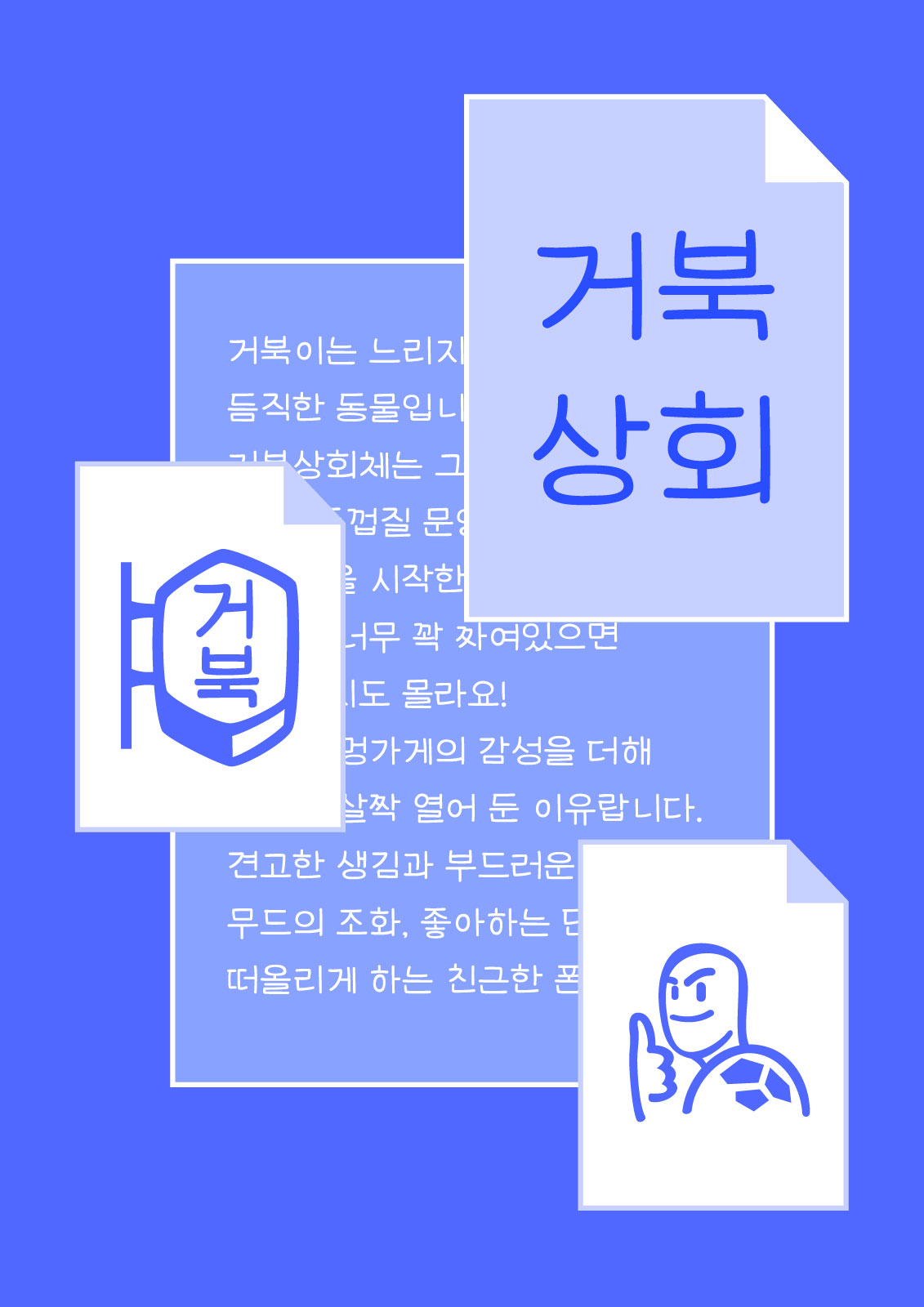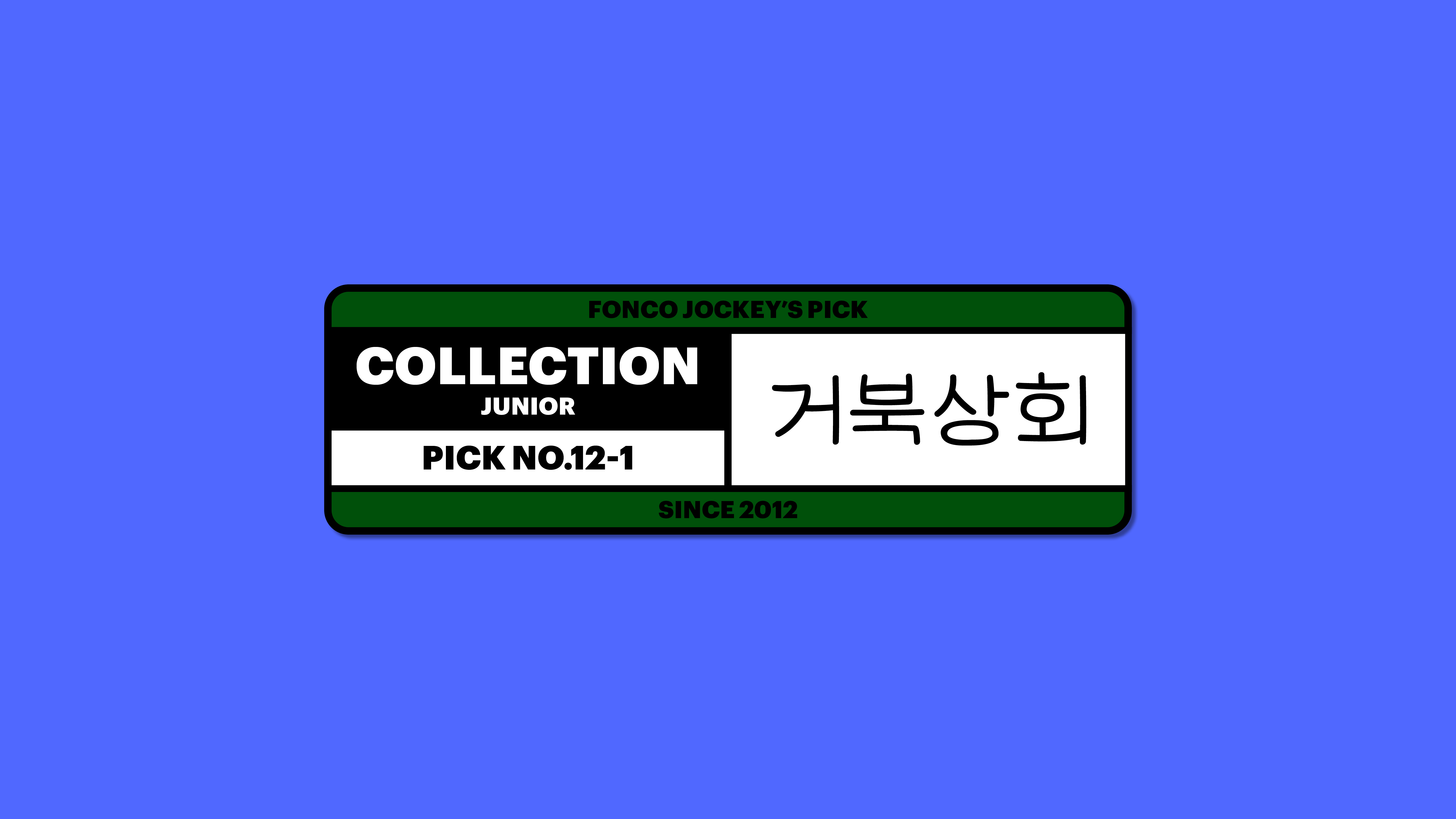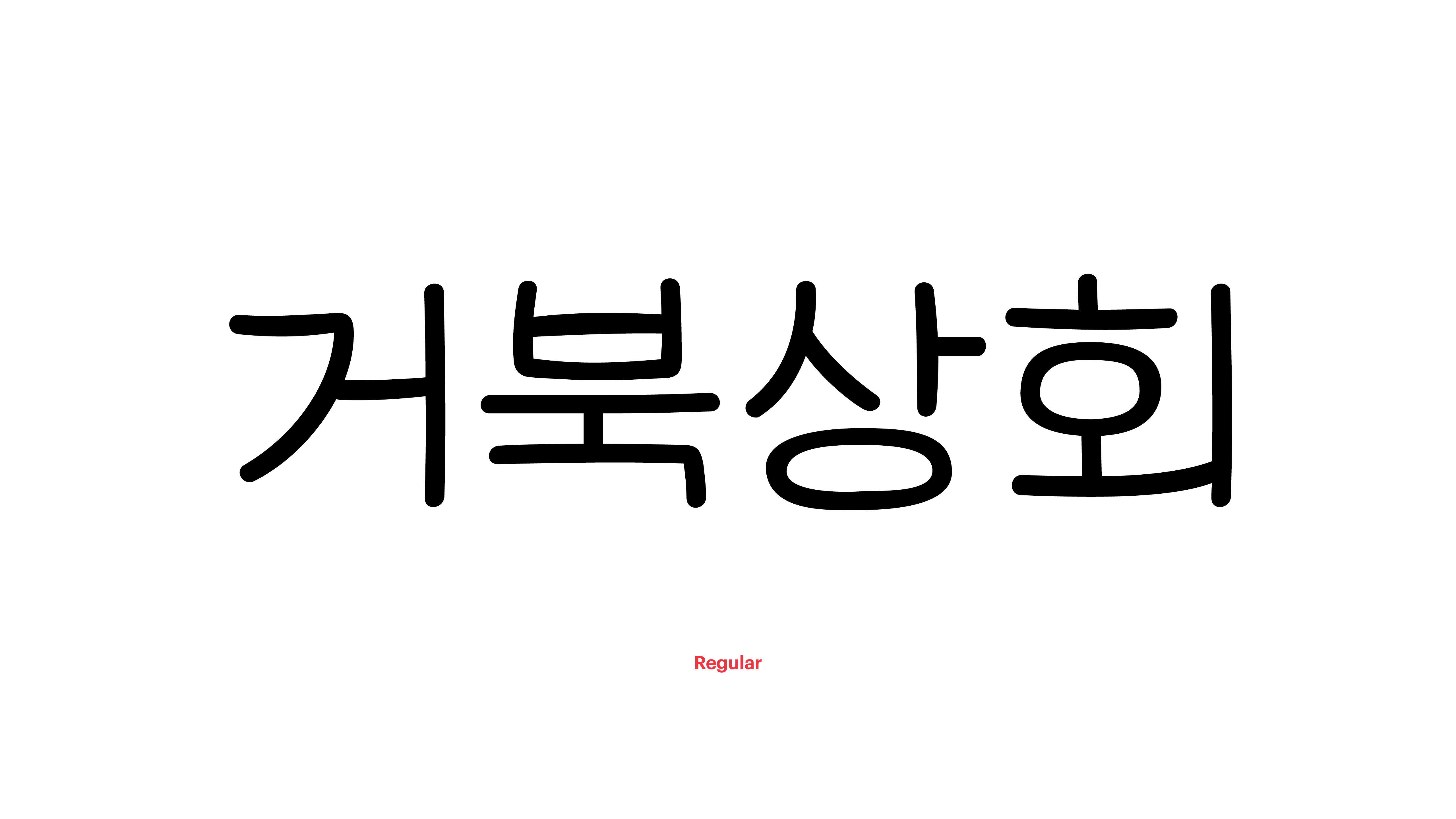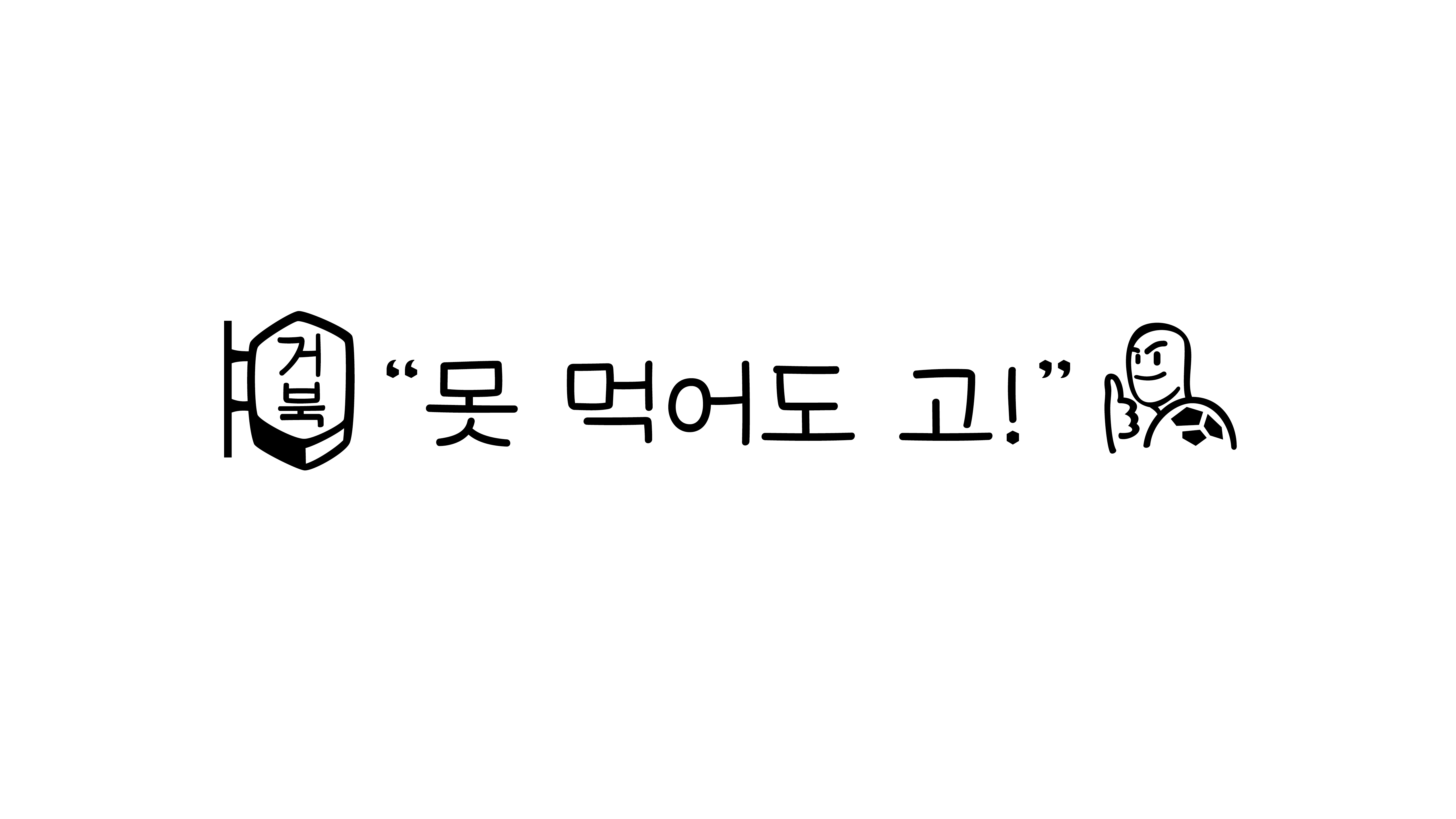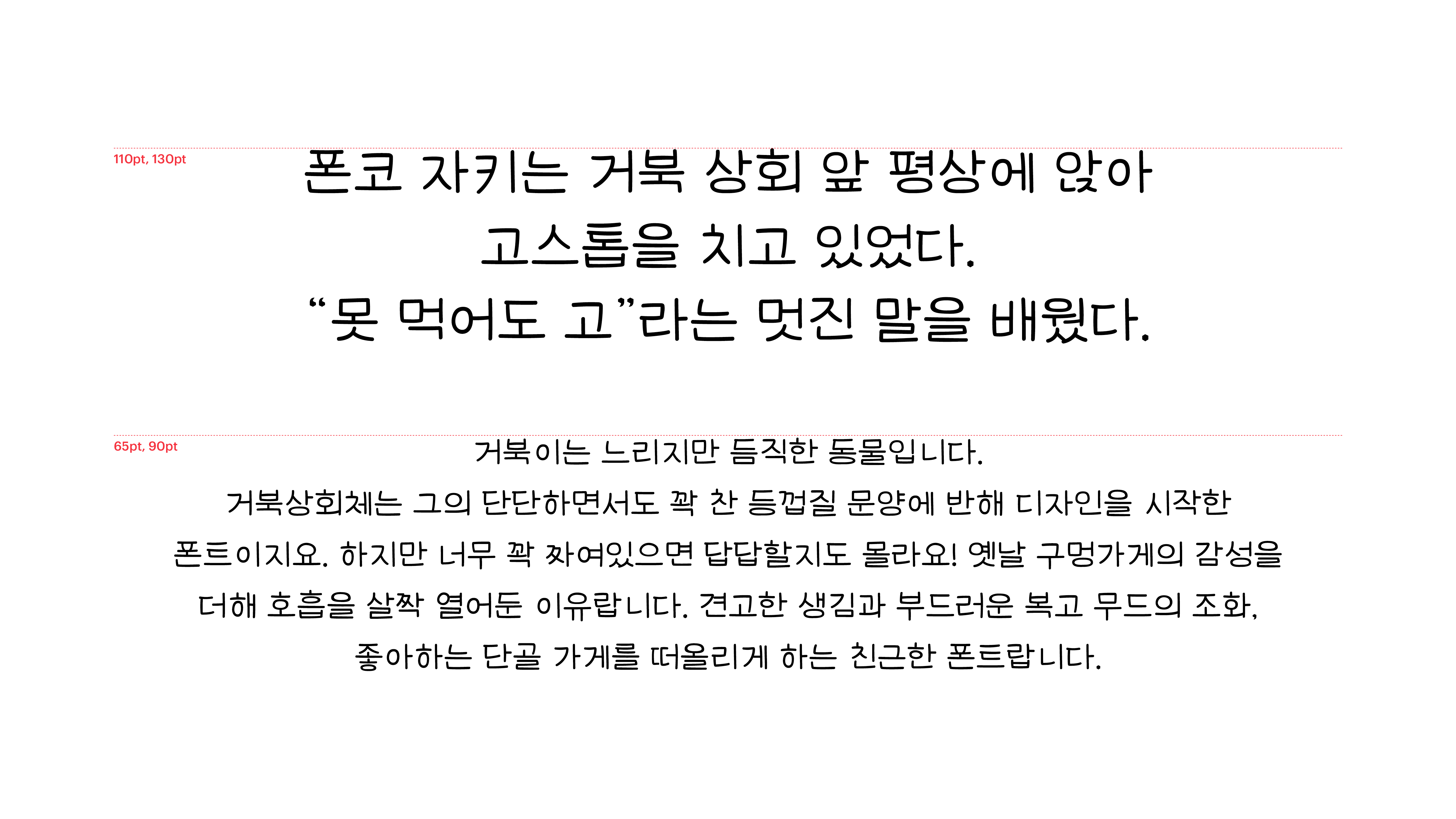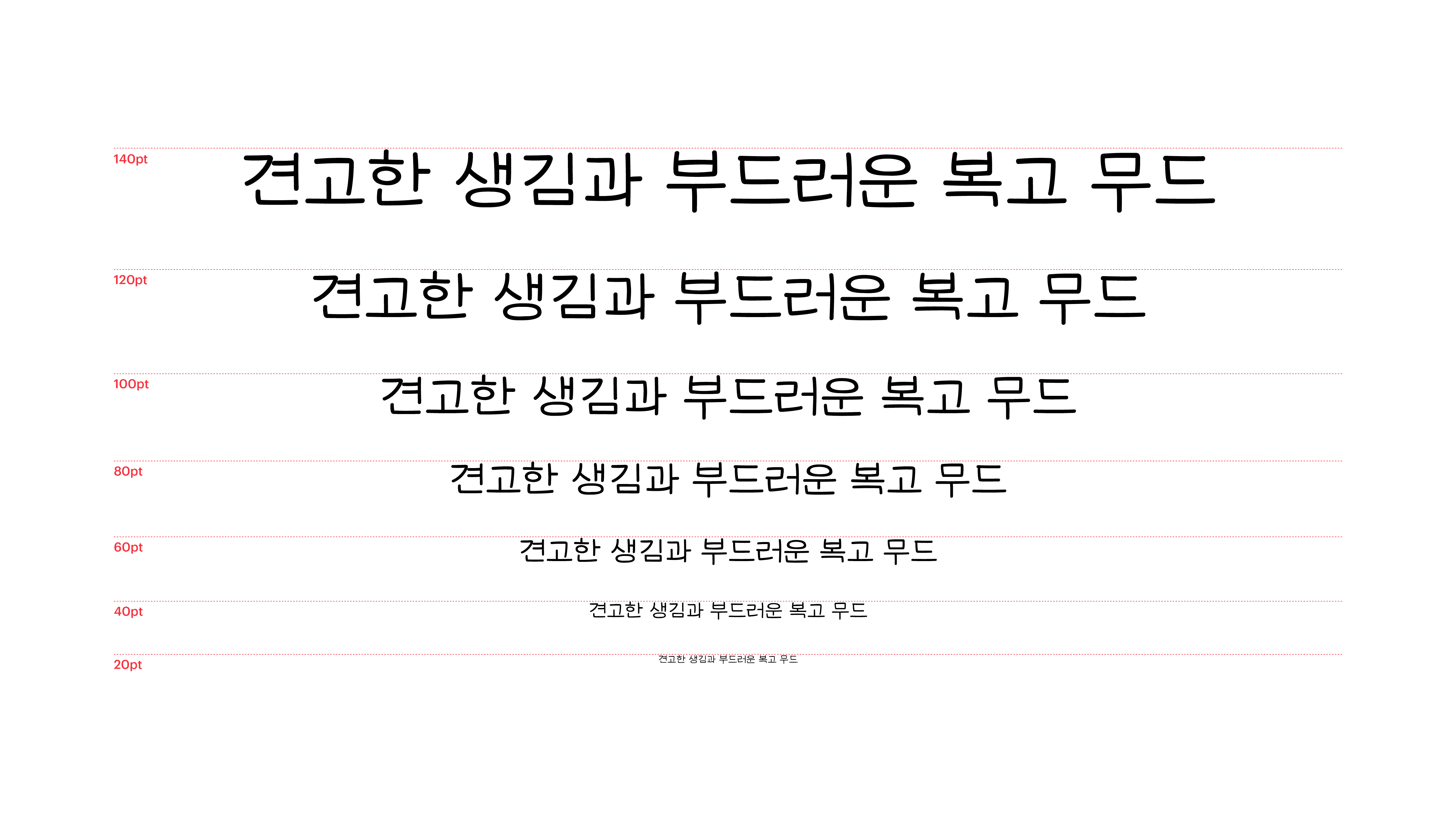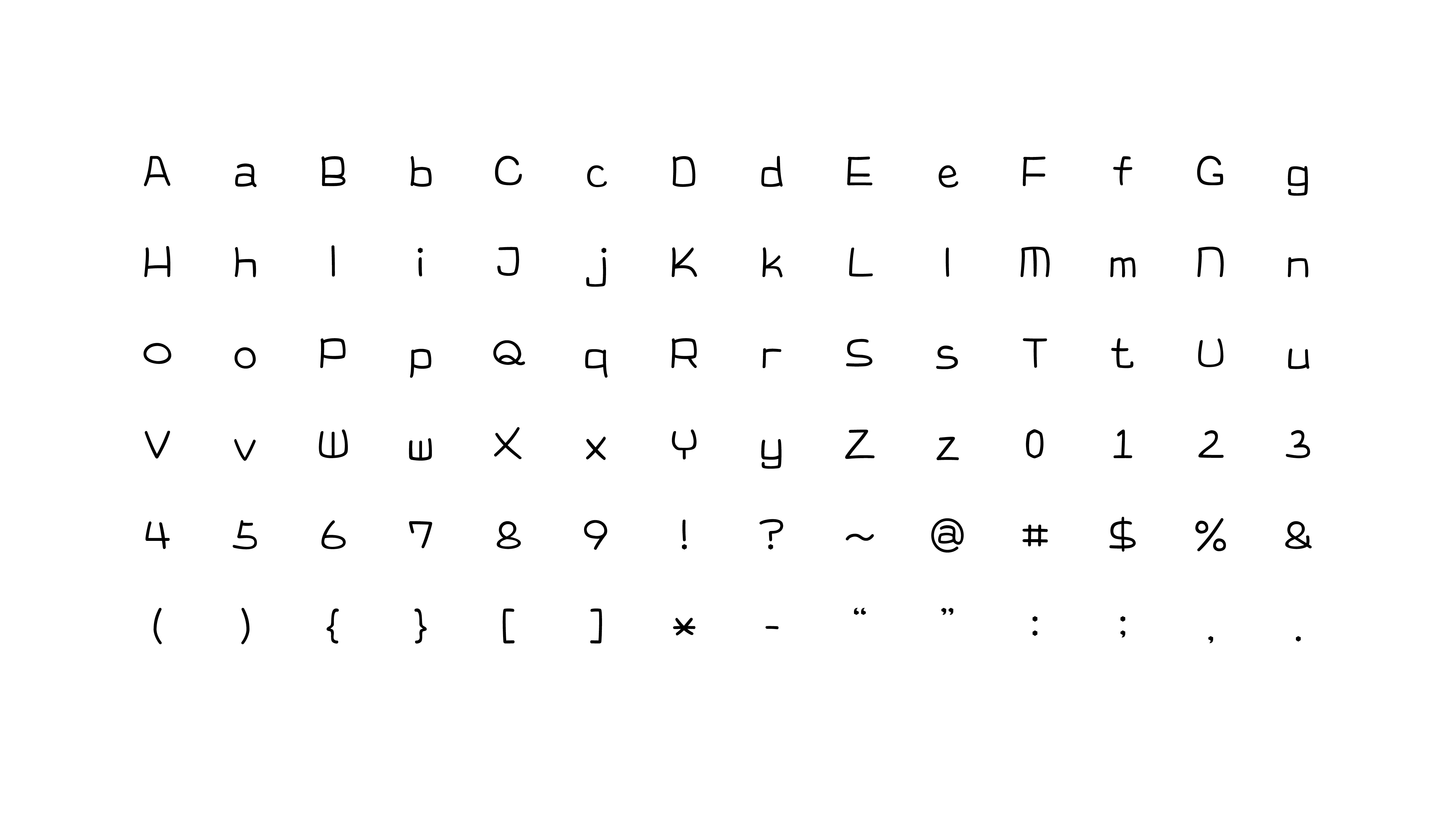
거북이는 느리지만 듬직한 동물입니다. 거북상회체는 그의 단단하면서도 꽉 찬 등껍질 문양에 반해 디자인을 시작한 폰트이지요. 하지만 너무 꽉 짜여있으면 답답할지도 몰라요! 옛날 구멍가게의 감성을 더해 호흡을 살짝 열어 둔 이유랍니다. 견고한 생김과 부드러운 복고 무드의 조화, 좋아하는 단골 가게를 떠올리게 하는 친근한 폰트랍니다.